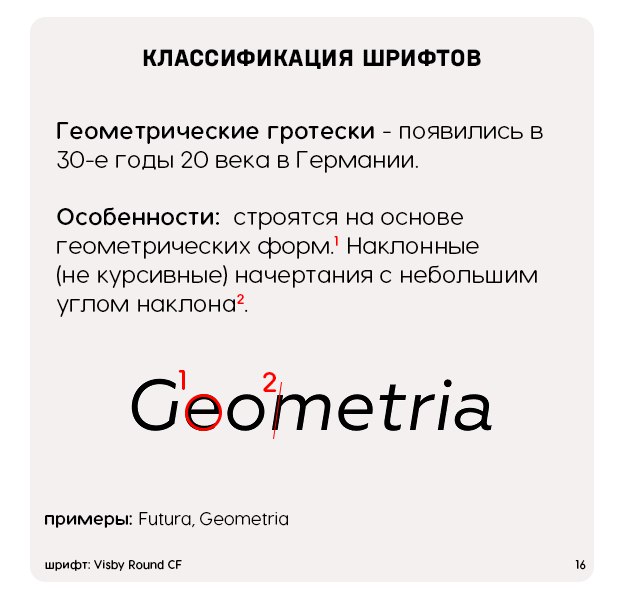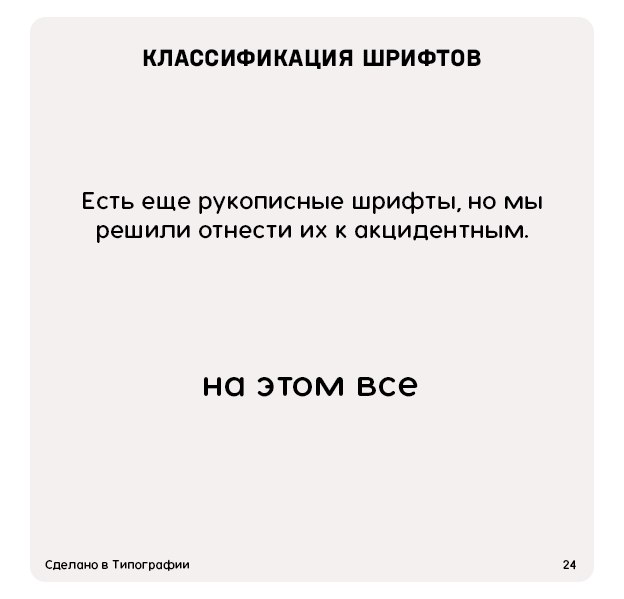
Роман Столбов создал наглядную классификацию шрифтов, наглядно разложив всю информацию по полочкам.
В инструкцию вошли все шрифты, начиная от антиквы, заканчивая старославянскими.